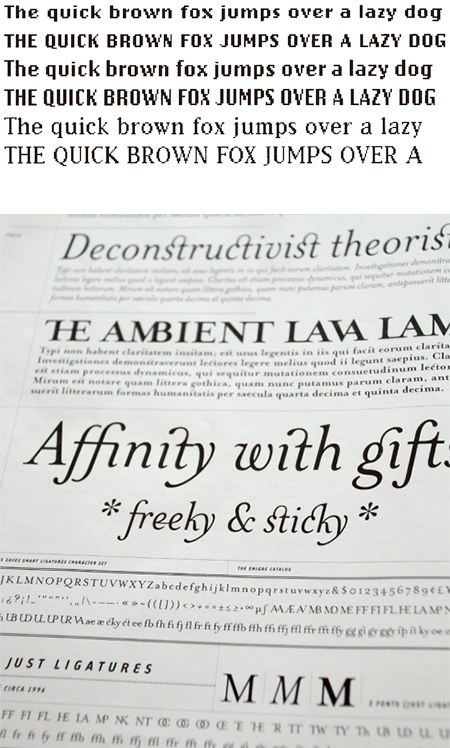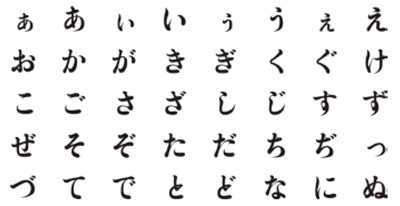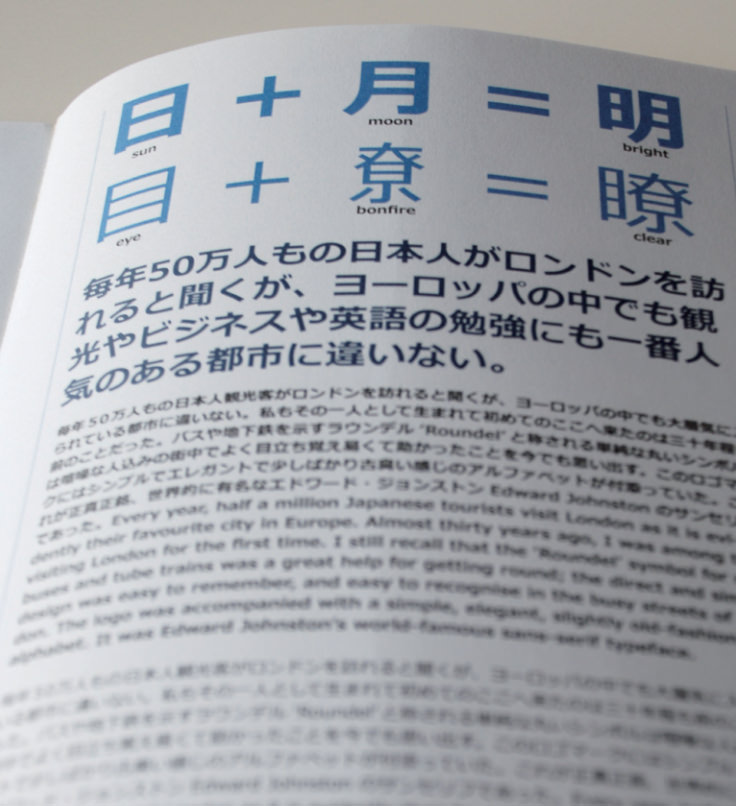
第七回 技 術 と 方 法 4 コ ン ピ ュ ー タ ・ 下
タイポグラフィにはふたつのジャンルがあります。ひとつは、ここで取り上げているような組版を中心とした文字による表現法で、もうひとつはタイプフェイスデザイン、つまり書体設計です。タイポグラファーとタイプフェイスデザイナーは違う仕事ですが、通常、両方を含んでタイポグラフィと呼ぶことが多いようです。わかりやすく定義すると、文字をつくることと使うこと。このふたつが広義のタイポグラフィと言っていいでしょう。
文字をつくる人は長く活版印刷所の中におり、日本に書体デザイナーと呼べる職能が現れるのは写植以降のことです。ヨーロッパの活字書体は比較的出自や作者がはっきりしていますが、字数の問題もあるのでしょう、日本では匿名の場合が多く、組織の仕事といった印象があります。しかし、物理的な文字をつくる必要がない写植技術下において、タイプフェイスデザインは一気に花開きます。第五回でも述べたように「タイポス」や「ゴナ」といった新しい書体が生まれ、モリサワ・タイプフェイスコンテストなどのコンクールで、書体デザイナーへの道も拓かれていきました。書体制作の仕事がデザイナー個人の資質に帰するようになったのは、このころのことです。
写植書体が活字より飛躍的に開発しやすくなったとはいえ、デザイン以降の製作部分はまだまだ資本の手にゆだねなければならないものでした。しかし、Apple Macintoshとフォント作成ソフトの登場により、事情は劇的に変化します。商業印刷に耐えうるアウトラインフォントを「文字を使う」側であったグラフィックデザイナーがつくれるようになったのです。それもやはり、文字数も少なく扱う情報量も小さいラテンアルファベットからはじまりました。
書体
デザイン
の新潮流
80年代中ごろ、デジタルタイポグラフィは、アップルコンピュータを生んだアメリカ西海岸のDIY(Do It Youeself)精神とロンドンの先進的かつ伝統的なグラフィックデザインが結びつくことで開花します。
インディペンデントなレコードジャケットのデザインなどで知られていたネヴィル・ブロディは、『FACE』誌のオリジナルフォントを駆使したアートディレクションで一躍脚光を浴び、デザイナーズフォントを先導する役割を果たしました。また、自らタイポグラフィのプロジェクト「FUSE」を主催し、パーソナルな書体デザインを推進しました。ブロディのあとには、ジョナサン・バーンブルックらが続き、ロンドンのみならず、アメリカや日本にも多大な影響を及ぼしました。
デザイナーズフォントは、70年代後半のパンクやニューウェイヴにはじまる音楽シーン、やはりロンドンの「i-Dマガジン」などにみられるストリートファッション、ヒップホップやテクノといったクラブカルチャーなど、サブカルチャーと地続きにあったものです。これまでの活字や写植書体にはない、ボトムアップの文化がそこにありました。
アメリカ、バークレーでは、84年にルディ・バンダーランスとズザーナ・リッコによる「エミグレ(エミグレ・グラフィクス)」が設立されました。タイポグラフィをメインとしたグラフィックマガジン『Emigure』も同年に発行され、タイプ・ファウンドリーとしての役割も担いました。
エミグレはビットマップフォントにはじまり、アウトラインフォントにおいても斬新なデザインのフォントを発表し、オルタナティヴなタイプフェイスデザインを実践していましたが、96年に発表した「ミセス・イーヴス」によって、伝統的なタイポグラフィ界にも受け入れられるようになりました。「ミセス・イーヴス」は、ジョン・バスカヴィルの妻の名を冠した改刻書体です。
そのほかに、MetaやInfoといった新標準ともいえる書体を手掛けたエリック・スピーカーマンが主宰する「FontFont」、70年代『RollingStone』誌のアートディレクターとして知られるロジャー・ブラック率いる「The Font Bureau」、先鋭的な制作集団の「T-29」などがよく知られるところです。
日本におけるパーソナルなフォント制作は、ロンドンからの逆輸入による「カタカナフォント」で注目されました。ロンドンのストリートシーンにおける日本の文字、特にカタカナの流行に影響を受け、新進のデザイナーたちがカタカナフォントをつくって発表しはじめます。カタカナだけなら、欧文と同じ1バイトで処理ができ、「Fontgrapher」など、パーソナルな欧文フォント作成ソフトが使えたのです。印象的なデザイナーとして、「レヂスターフォント」「ポリエステルフォント」など、シーンをリードする書体を矢継ぎ早に発表したミヤヂマタカフミの名前を挙げることができます。
残念ながらカタカナフォントは一過性のブームに終わってしまいましたが、味岡伸太郎氏が中心となって進めている「Font1000」のプロジェクトなど、グラフィックデザイナーの手による意欲的な書体制作は今も続いています。
Typeface Six, 1986
ネヴィル・ブロディ
(上)Emigre, 1985
(下)Mrs. Eaves Smart Ligatures, 1996
ズザーナ・リッコ
(上)レヂスターフォント, 1995
(下)ポリエステルフォント, 1996
ミヤヂマタカフミ
伝統への
回帰
手元に4冊の和文デジタル書体の総合見本帳があります。古い順から紹介すると、『和文電子活字綜合見本帳』(1999年、朗文堂)、『DTP World別冊 デザイナーのためのフォントスタイルブック2004』(2004年、ワークスコーポレーション)、『アイデア別冊 基本日本語活字集成 OpenType版』(2007年、誠文堂新光社)、『フォントブック[和文基本書体編]』(2008年、毎日コミュニケーションズ)。判型に違いはありますが、まるで倍々ゲームのように分厚くなっています。
収録書体数は、『和文電子活字綜合見本帳』約1250書体、『フォントスタイルブック2004』1377書体(和文フォント)、『日本語活字集成』約1650書体、『フォントブック』558書体と単純に増えているわけではありません。しかし、おおよそ20年前にわずか数書体でスタートしたデジタルフォントが、10年後の90年代後半には1000書体を数え、さらにその10年後の現在は2000に届こうという、とんでもないスピードで開発されていることがわかります。
見本帳をぱらぱらめくっていると、99年のものは(見本帳のレイアウト体裁もあって)まだ写植書体見本帳とたいして違わない印象なのですが、年を経るにつれクラシックな文字が目につくことに気づきます。実際、04年発行の見本帳には、字游工房の「游築見出し明朝」や「游築初号ゴシックかな」、同社のデザインによる大日本スクリーン製造の「游築仮名」シリーズなどの活字の源流ともいえる築地体の改刻書体が登場しています。07年刊行本には、復刻書体のシリーズ「日本の活字書体名作精選」(大日本スクリーン製造)やフォントワークスの「筑紫明朝」なども掲載され、この間に改刻書体がひとつのジャンルを築いたことがわかります。オールドかな、小がな、アンチック体の復活や、写植特有の文字のボケ足を再現したモリサワの「A1明朝体」などもこの流れの上にあるものと考えていいでしょう。
『日本語活字集成』の巻頭で小宮山博史氏が日本語書体の分類を試みていますが、そこでは、こういった明治の活字を源流に抱く改刻書体を、基本書体のひとつ(明朝体─オールドスタイル)としてカテゴライズしています。
デジタル化された書体制作の技術によって、デザイナーがオリジナル書体を自由にデザインできるようになっただけでなく、こういった活字資産も高度にフォント化できるようになりました。その背景には、コンピュータによって喚起されたタイポグラフィへの興味によって、これまでの地道な活字研究に注目が集まったことがあります。電子テクノロジーは未来を想起させるだけでなく、過去を振り返る契機にもなっていたのです。
游築初号かな, 2004
字游工房
デジタル
メディア
の文字
デジタルフォントは印刷用の文字だけでなく、デジタルメディア、つまり画面表示用の文字としても開発されています。オンスクリーンの文字はビットマップフォントが主流でしたが、ここ数年、アウトライン表示に切り替わりつつあります。理由として、ディスプレイが高解像度になったこと、ラスタライズの技術が熟してきたことなどが挙げられます。
コンピュータではMacOSが印刷書体としても評価の高い「ヒラギノ」をデバイスフォントとして採用し、マイクロソフトはWindowsVistaからClearTypeに対応した「メイリオ」を搭載しました。ClearTypeはWindowsXPから用いられているアンチエイリアシングの技術です。
携帯電話でもビットマップフォントからアウトラインフォントへの切り替えが進められています。新ゴをはじめとしたモリサワ書体を三分の一以下の容量に軽量化し、専用の高速ラスタライザと共に提供する「KeiType」が、富士通や三菱電機の携帯電話に搭載されたのは記憶に新しいところです。
デジタルメディアの場合、常にフォントのデータ量が問題になります。そのため、アウトラインの制御点をいかに少なくして文字のかたちを整えるかが書体の善し悪しを決めるポイントとなります。デザイン誌『AXIS』専用に開発された「AXISフォント」は、そういった意味で成功した数少ない例でしょう。
たとえば「ヒラギノ角ゴシックProW3」は8.9MB、「平成角ゴシック」は3.5MBですが、「AXISスタンダード・レギュラー」は1.8MBしかありません。雑誌のエクスクルーシヴフォントとしての経緯しか語られてこなかった「AXISフォント」ですが、実はスクリーンフォントをにらんでの開発であったことがわかります。書体設計もデザイナーの技能だけではなく、アートディレクターの才気が問われる時代に入ったということなのでしょう。
近年のタイプフェイスデザイン研究では、CTPにおける文字印刷と高解像度ディスプレイの文字表示とは、書体設計において同様の対応が可能であるという結論になりつつあります。印刷とスクリーン表示に同じ文字を使えることで、メディアデザインとタイポグラフィについて新たな考察が必要になってくるでしょう。
これまで、オンスクリーンでのタイポグラフィはあまり語られることがなく、どちらかといえばあきらめ気分が蔓延していた分野です。しかし、紙よりディスプレイで文字を読むことの方が多くなってきつつある今、文字による表現の可能性が拡がったことは歓迎すべきことです。
開発中のメイリオ(当時「明瞭」)が掲載された
『Now read this』(Microsoft, 2004)
KeiType, 2007
モリサワ
AXIS Font Standard EL, 2001
AXIS Inc, タイププロジェクト
オープン
タイプと
書体設計
の将来
和文のポストスクリプトフォントはこの短い歴史の中で、二度大きくフォーマットを変えました。ポストスクリプトフォントは、欧文(ラテンアルファベット)を前提に開発されたものですから、当初256文字(1バイト)しか扱えませんでした。しかし、日本語を表記するには数千字が必要です。そこで、256文字ごとに小分けした1バイトフォント(Type1フォント)を合成(コンポジット)するかたちで、日本語などの2バイト言語用のフォーマットが作成されました。それが最初に普及したOCF(Original Composite Font)です。
次に、CID(Character IDentifier-Keyed)と呼ばれるフォーマットが登場します。CIDはフォント本体とマッピング情報を別のファイルで持っており、マッピング情報用のファイル(CMap)を取り替えれば、どんな文字コードにも対応できる利点がありました。また、文字のアウトライン化やエンベッドも可能で、フォントの用途を飛躍的に拡げました。
現在主流となっているのは、マイクロソフト社とアドビシステムズ社によって開発されたOTF(OpenTypeFont)です。OTFの特長として、大きく
- ユニコードを採用しているので最大約65000文字が登録可能
- TrueType, PostScrip双方に対応し、クロスプラットホームを実現
- ダイナミックダウンロードによってプリンタフォントが不要
の三つを挙げることができます。
異体字を搭載できたり、文字化けが減ったり、解像度の制限がなくなったりという実利があるのはもちろんですが、書体設計そのものを根源から揺るがすようなことが起こっています。
OTF対応のアプリケーションにはさまざまなメニューがあります。数字の字形や縦組み横組みに対応する仮名の自動選択はもとより、「前後関係に依存する字形」を選択することもできます。
これまで、フォントとなったひとつの文字のかたちはひとつと決まっていました。しかし、文字をたくさん格納できる技術は、さまざまな異体字の併存を可能にします。日本語では旧字に使われることが多いのですが、縦組み用、横組み用、ルビ用など字形を調整した仮名を同じフォント内に持つこともできます。それだけではなく、前後の文字とのつながりによってハネやハライなどを調整した文字を表示することも可能になりました。「あい」と「あう」の「あ」を、違うかたちで表現することができるということです。欧文フォントでは「Caflisch Script」など、すでにこの機能を備えた書体が散見されます。
書体ごとの揺るぎないかたちを完成させることが書体設計の目標のひとつでしたが、今後は、文章になったときの文字の変化を考えに含めて、固有の“かたち”ではなく、変化のアルゴリズムを設計することが必要になってくるでしょう。
スタンプのように同じかたちが繰り返されることを奇異に感じたのか、考えてみれば、グーテンベルクのブラックレターや嵯峨本の連綿体など、写本や書写をお手本とせざるを得なかった最初の印刷書体は、微妙に違うかたちの同じ文字をたくさん持っていました。コンピュータを活用することで手のぬくもりがかえってくるかも知れません。
Caflisch Script Pro に収められたさまざまな"p"
42行聖書に使われたグーテンベルグ活字
『Typographie』Emil Ruder, Nibbliより
嵯峨本『伊勢物語』(近畿大学中央図書館蔵)より採集された連綿木活字の「あ」の一部
「嵯峨本の印刷技法の解明とビジュアル的復元による仮想組版の試み」研究代表:鈴木広光 より